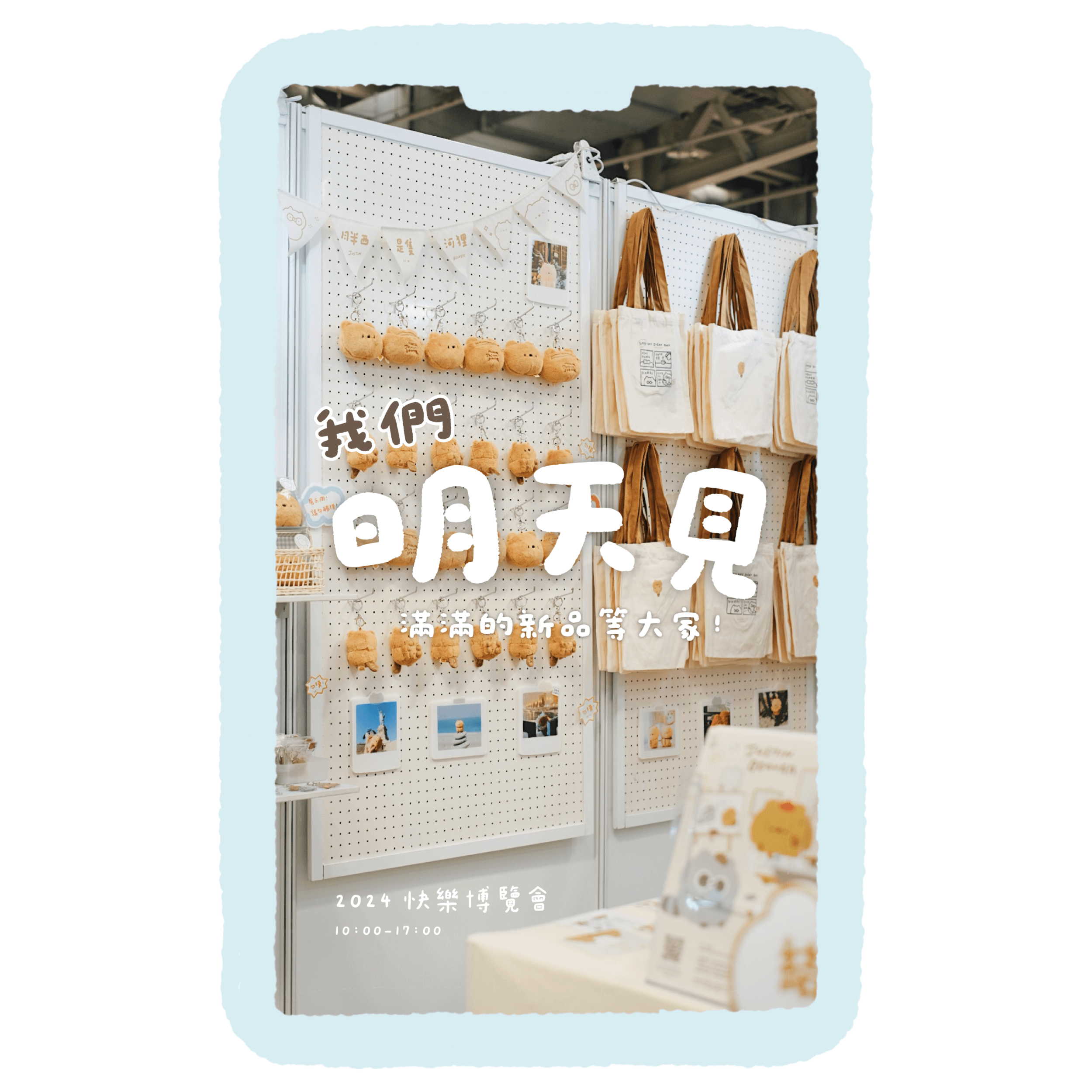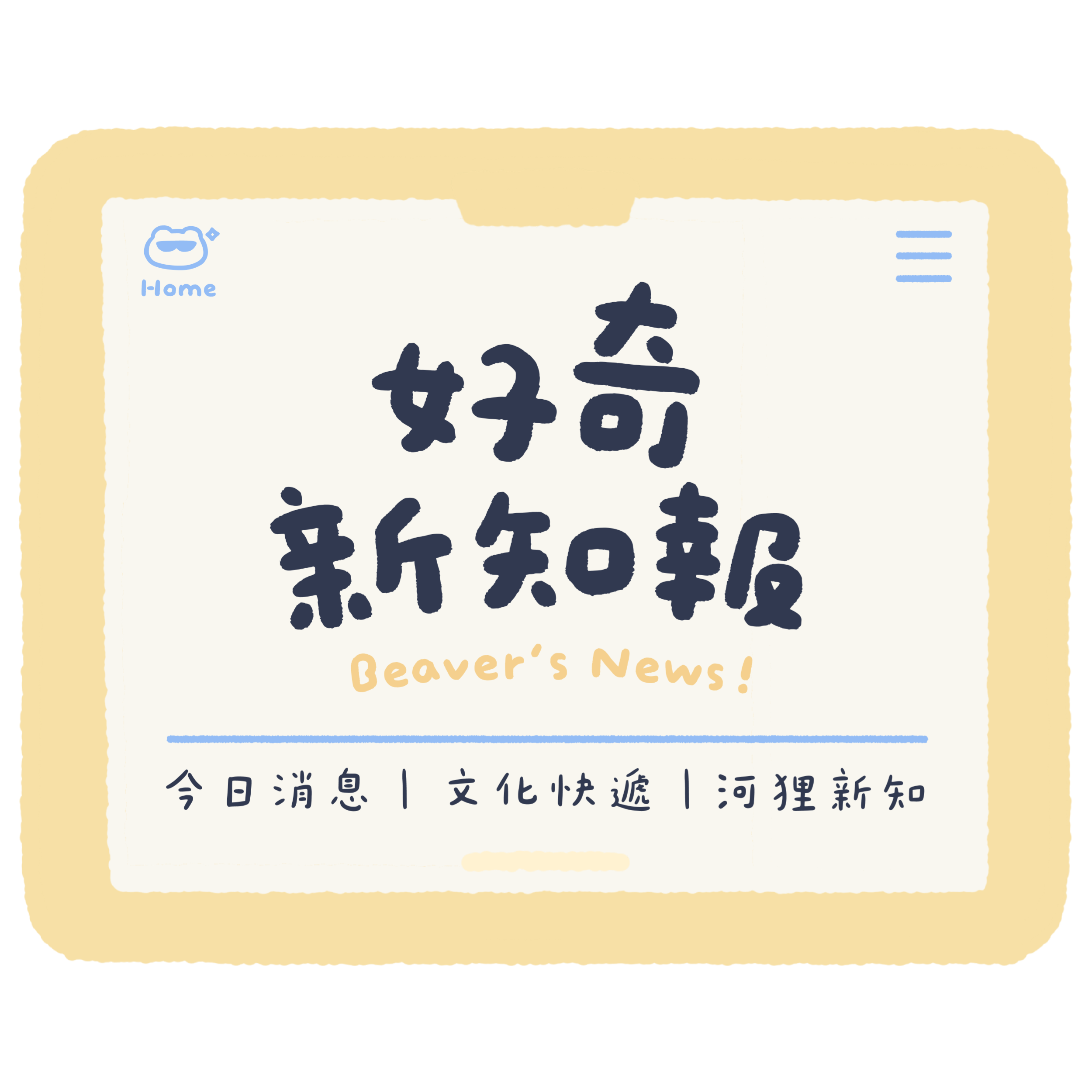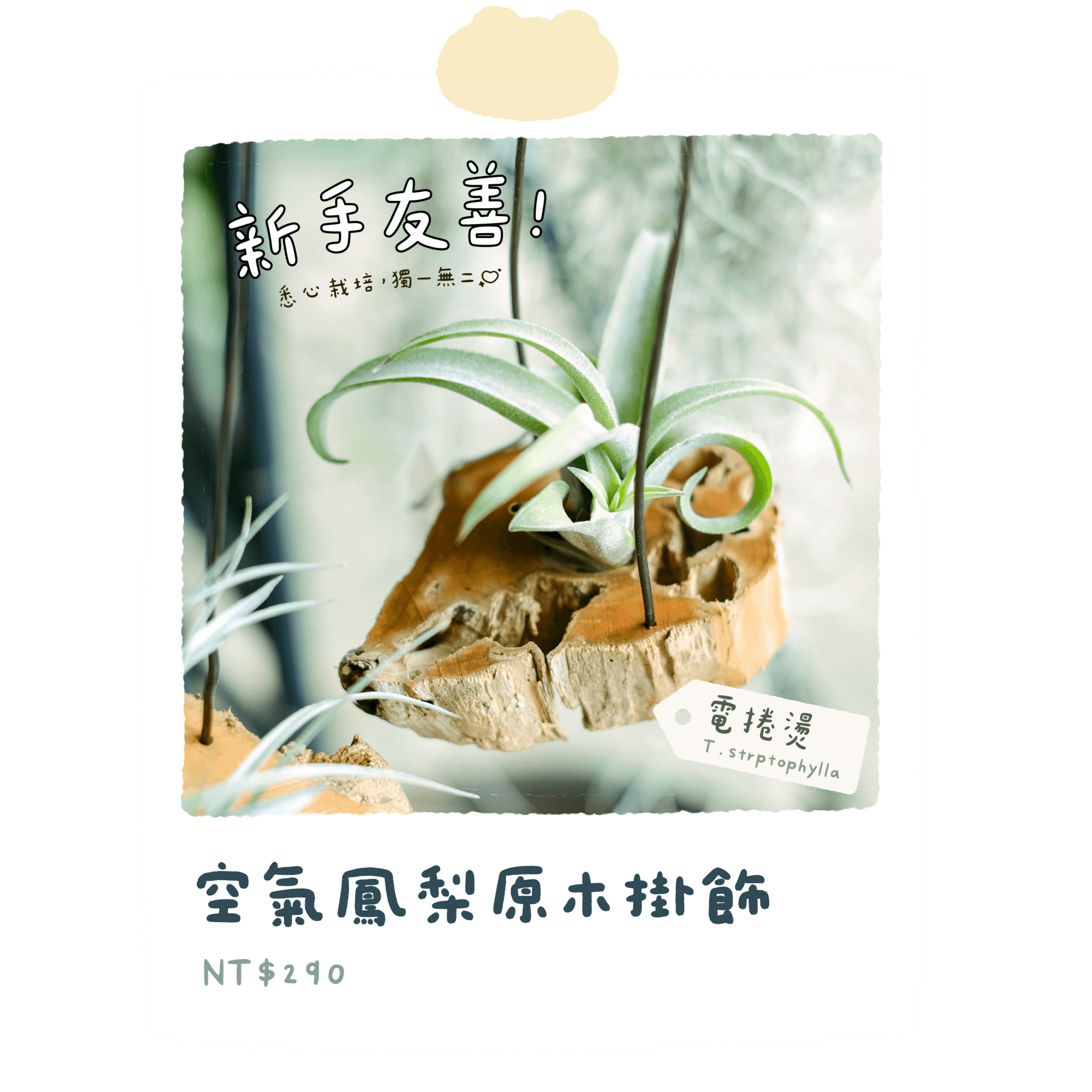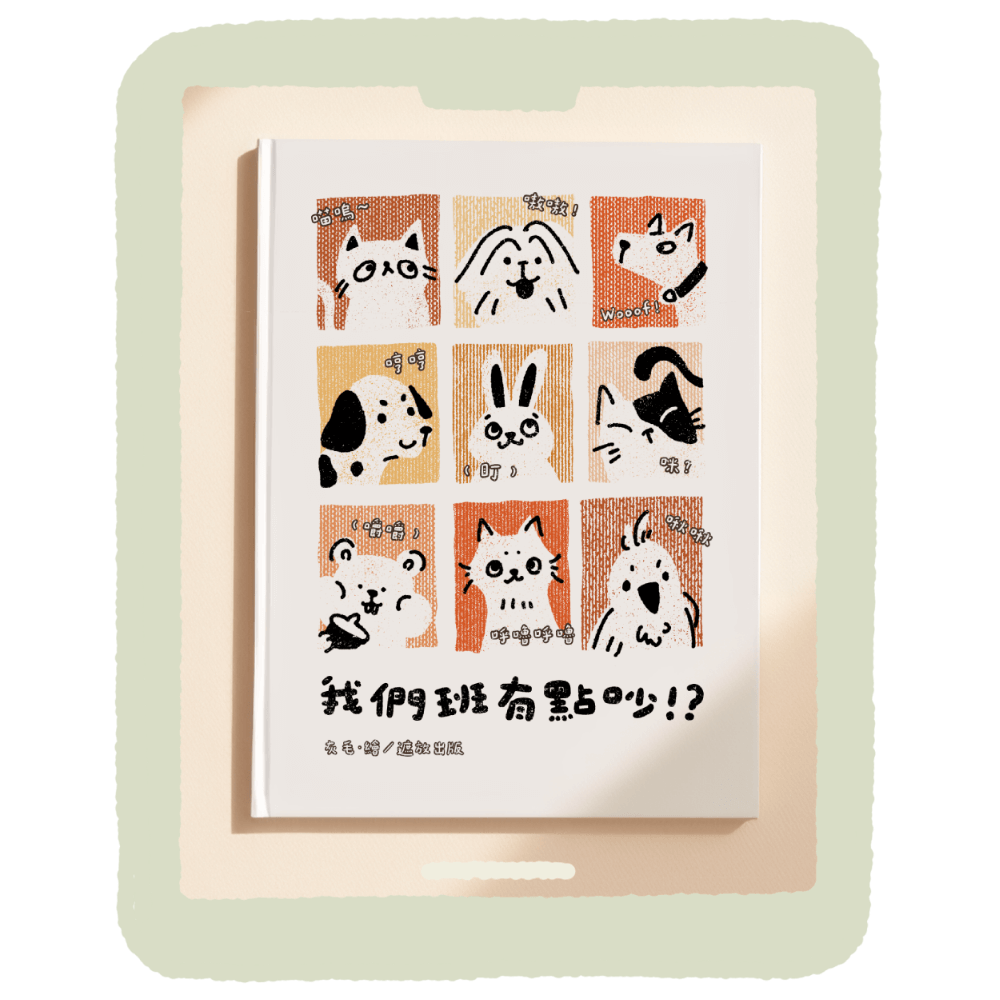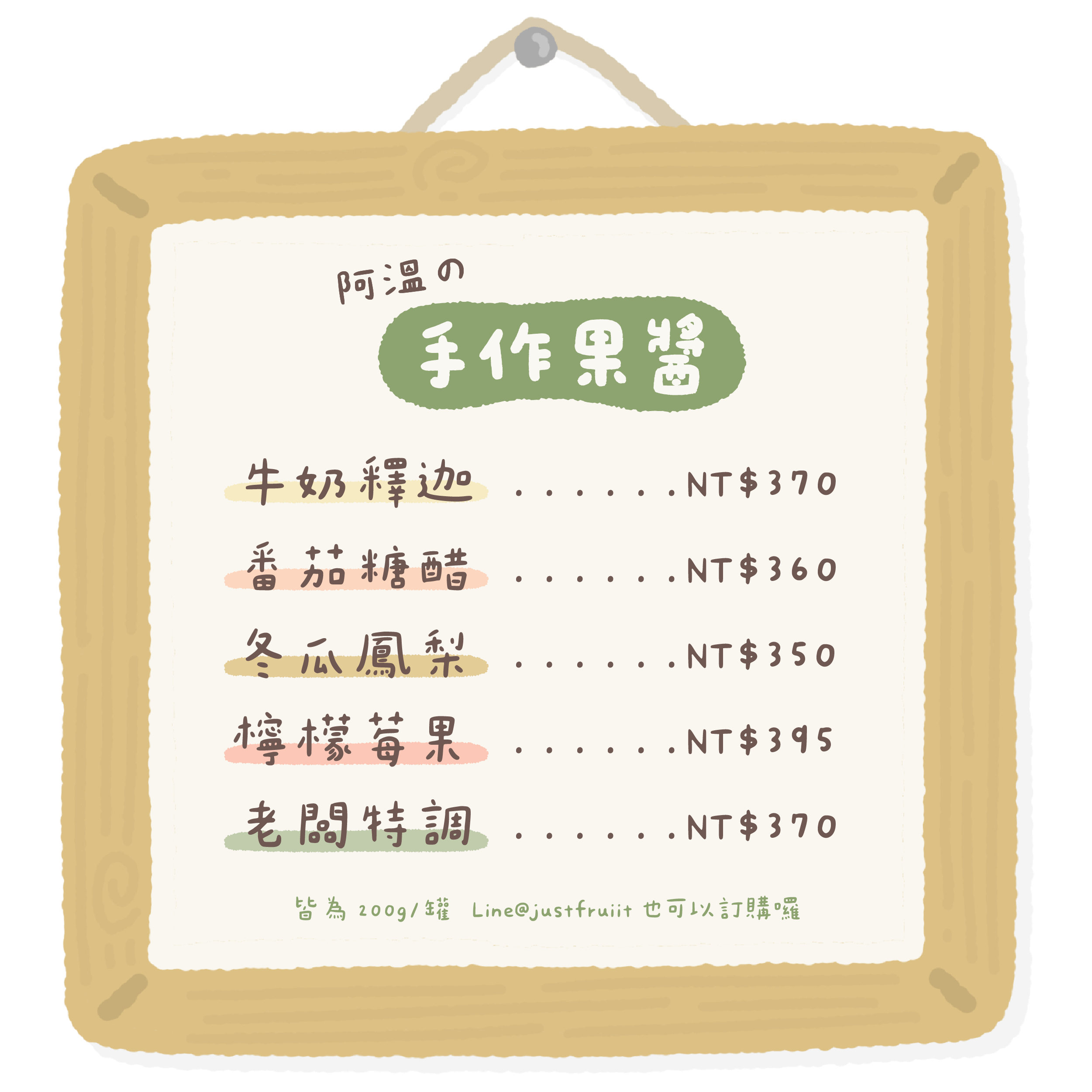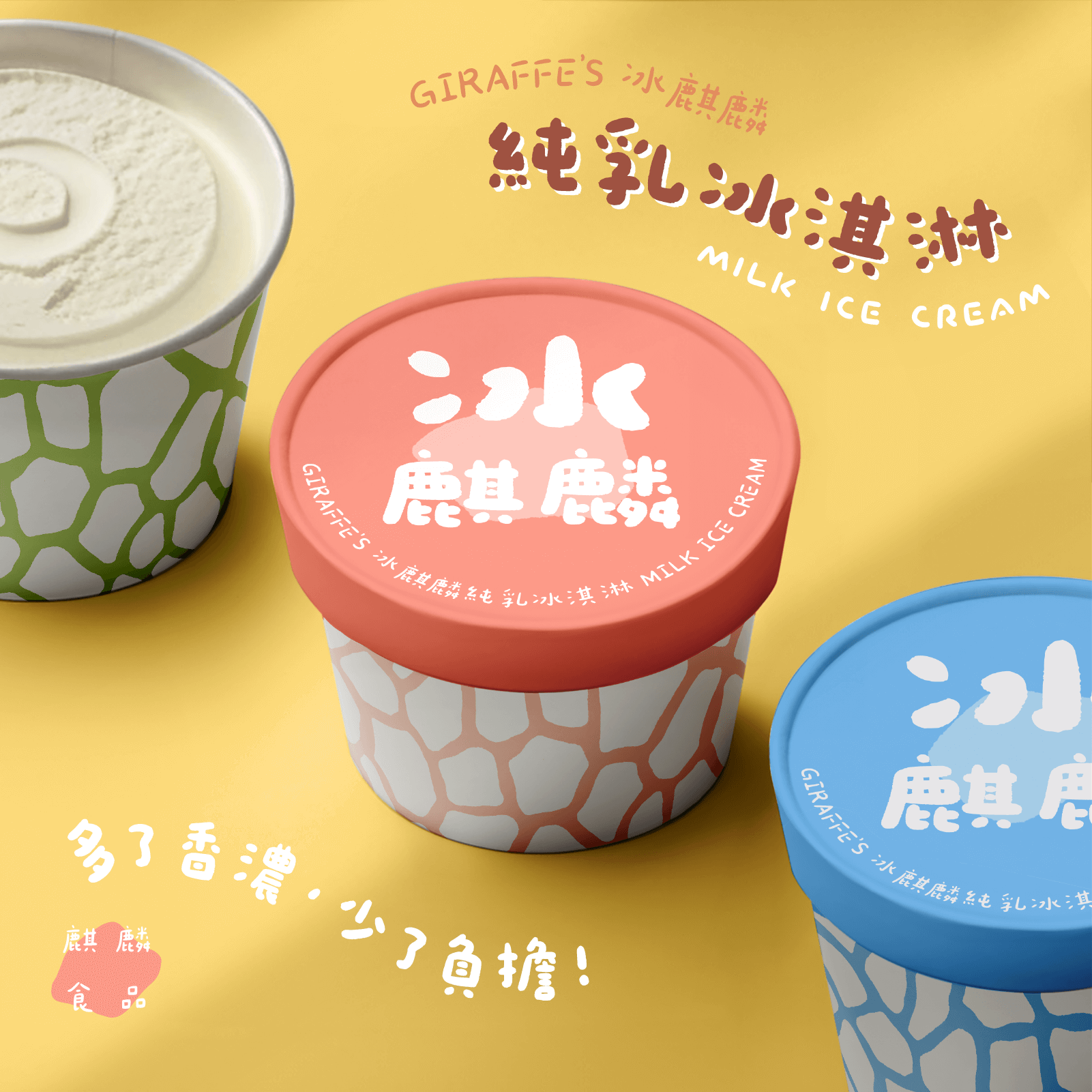
胖西手寫體
陪你寫下每一天,
把瑣事聊成大冒險!
蓬蓬 Fluffy
認真
生活
軟軟可愛 自然空隙
深呼吸~~
飽滿
Q彈
瘦瘦 Slim
偶爾跌倒也大丈夫です🎵
小字優秀 生動又清晰
胖西手寫體有圓圓的身材,柔軟真誠。
有兩種粗細的可愛字體,還有專屬 Emoji!
\Hello!
拿杯茶坐坐/
你好(´・ω・)つ☕ 我是胖西,是隻河狸。
謝謝你來看我 💖雖然平常大家看到的是我的插畫、濾鏡、貼圖、饅頭⋯⋯但胖西手寫體是在我成為專職插畫家前就想做的事情!
請讓我陪你分享生活中的每個片刻,出現在 IG 限動、課表筆記、小標籤,療癒滿分。偶爾休息放個風,再一起面對新的每一天🔋⚡
有蓬蓬版與瘦瘦版,
一起用超級搭💯
下水前蓬蓬
下水後瘦瘦
胖西手寫體是獨特的手寫字家族,有兩種粗細,
標題內文互相搭配超實用!
只是製作不太容易 ก(ー̀ωー́ก)
胖西手寫體ㄉ
製作過程大揭秘🤓
Step1胖西努力中
Step2一些神仙幫忙
Step3加入可愛的事物
Step4不好說😶
Step5\完成了/
Step6交到你手裡💕
蓬蓬版跟瘦瘦版是分開寫ㄉ哦,不只是筆刷加粗,寫了好多字嗚
還有獨一無二的 Emoji,像這樣:🦫💕🪵😎
自然の生活感
\百搭/
胖西手寫體蓬蓬版與瘦瘦版各有 9000 以上字符,包含常用漢字、數字、注音符號等基本字符。另涵蓋台語、客語漢字及羅馬字以及原住民族語;日語假名及常用漢字、香港常用漢字⋯⋯等。支援 jf 7000 當務字集基本包、本土包、粵語包,歡迎參考 jf 7000 當務字集 的輸入測試區。
胖西手寫體 Emoji 可以用於下筆、Vivisticker、Inshot、Procreate、Illustrator 等常見軟體,用一般 Emoji 的輸入方式即可方便使用!蓬蓬版和瘦瘦版的 Emoji 是分開製作的,各支援約 100 種 Emoji。完整 Emoji 列表與使用方式請參考此頁。